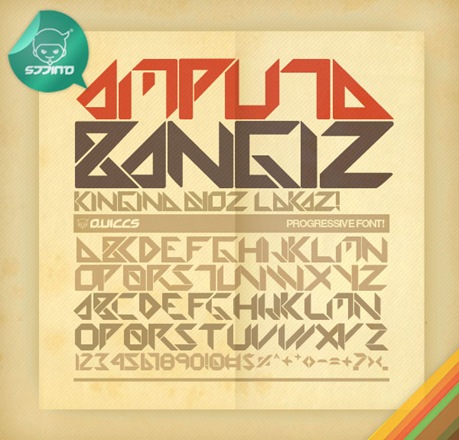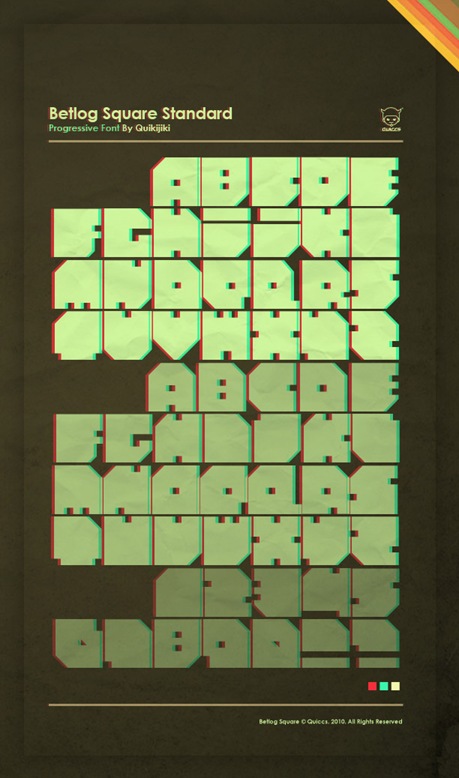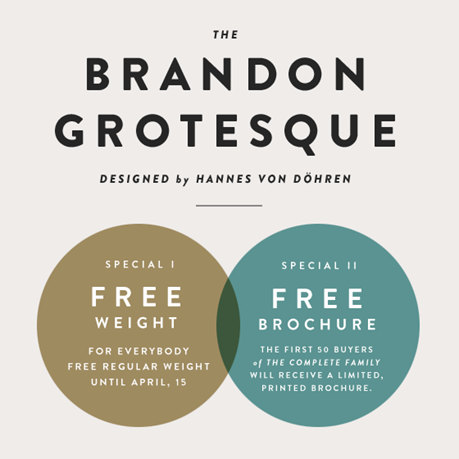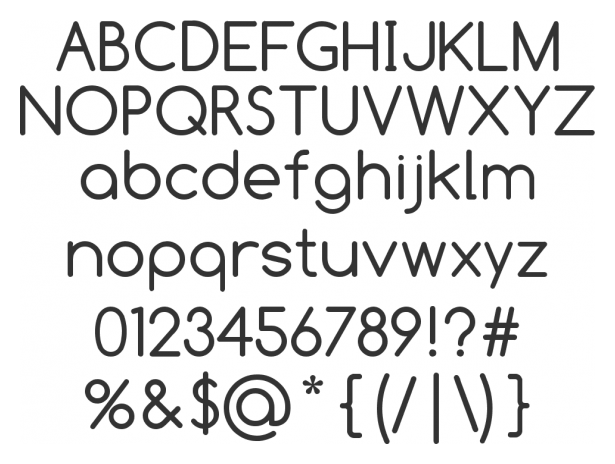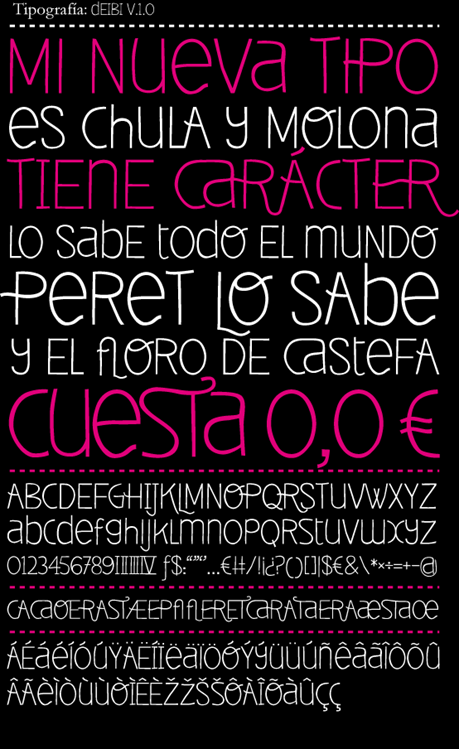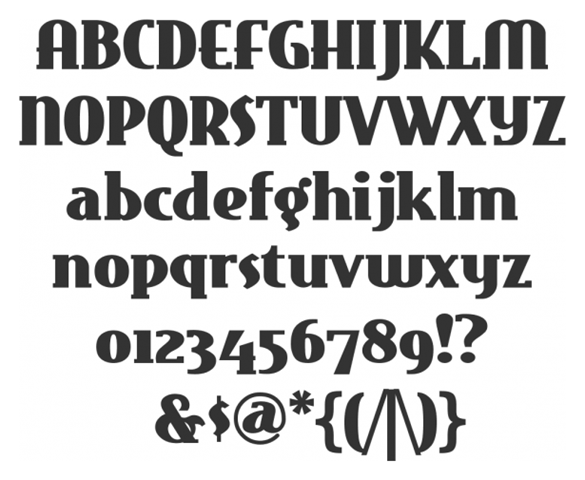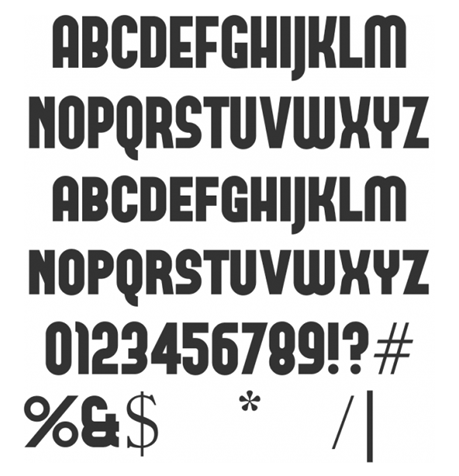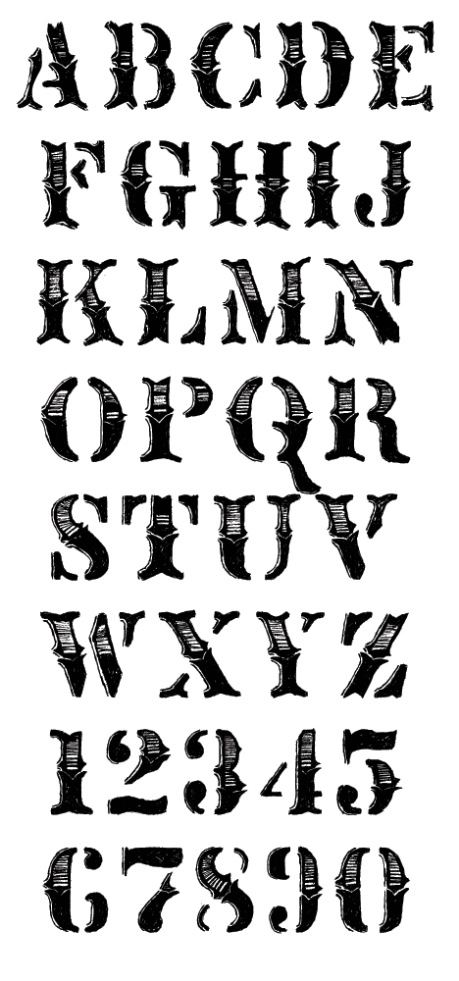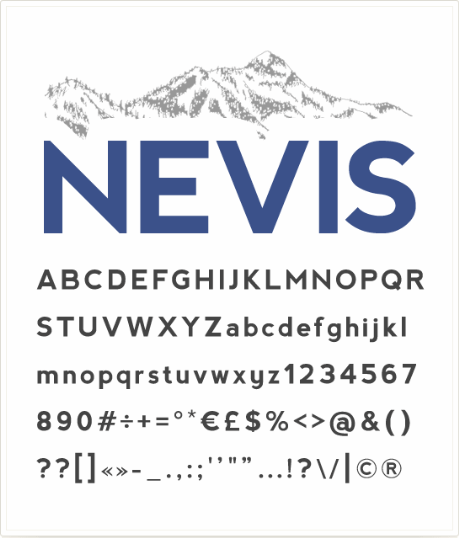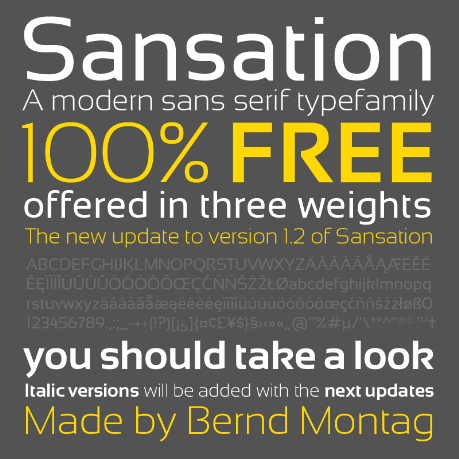
86 freie frische Fonts zum täglichen gestalten – Frohe Ostern!
86 frische Fonts zum täglichen gestalten. Für Vintage und Modern Design, für Fließtext, Überschriften, CD Cover, Visitenkarten, Logos, Broschüren usw. ist für jeden etwas dabei.
Clean Fonts
1. Walkway Font
2. Yanone Kaffeesatz
3. Jalane Light Font
4. Colaborate
5. Engel Light
6. Sansation Font
7. Vegur Font
8. Titillium
9. Anivers
10. Delicious
11. Museo Sans
12. Mentone
13. Aurulent Sans
14. Junction Font
15. Existence Light
16. Fontin
17. Comfortaa
18. Quicksand
19. Bonvenco
Vintage Fonts
20. Matchbook
21. Bazar Medium
22. Embossed Black Normal
23. Ugly Qua
24. Hillhouse
25. Shrewsburry Condensed Bold
26. Caslon Antique
27. Seaside Resort
28. Fontleroy Brown
29. Fusty Saddle
30. Dirty Ames
31. Bolton Font
32. Dymaxion
33. Riesling
34. Goudy Bookletter
35. Opera Lyrics Smooth
36. Carnivalee Freakshow
37. Circus Ornate